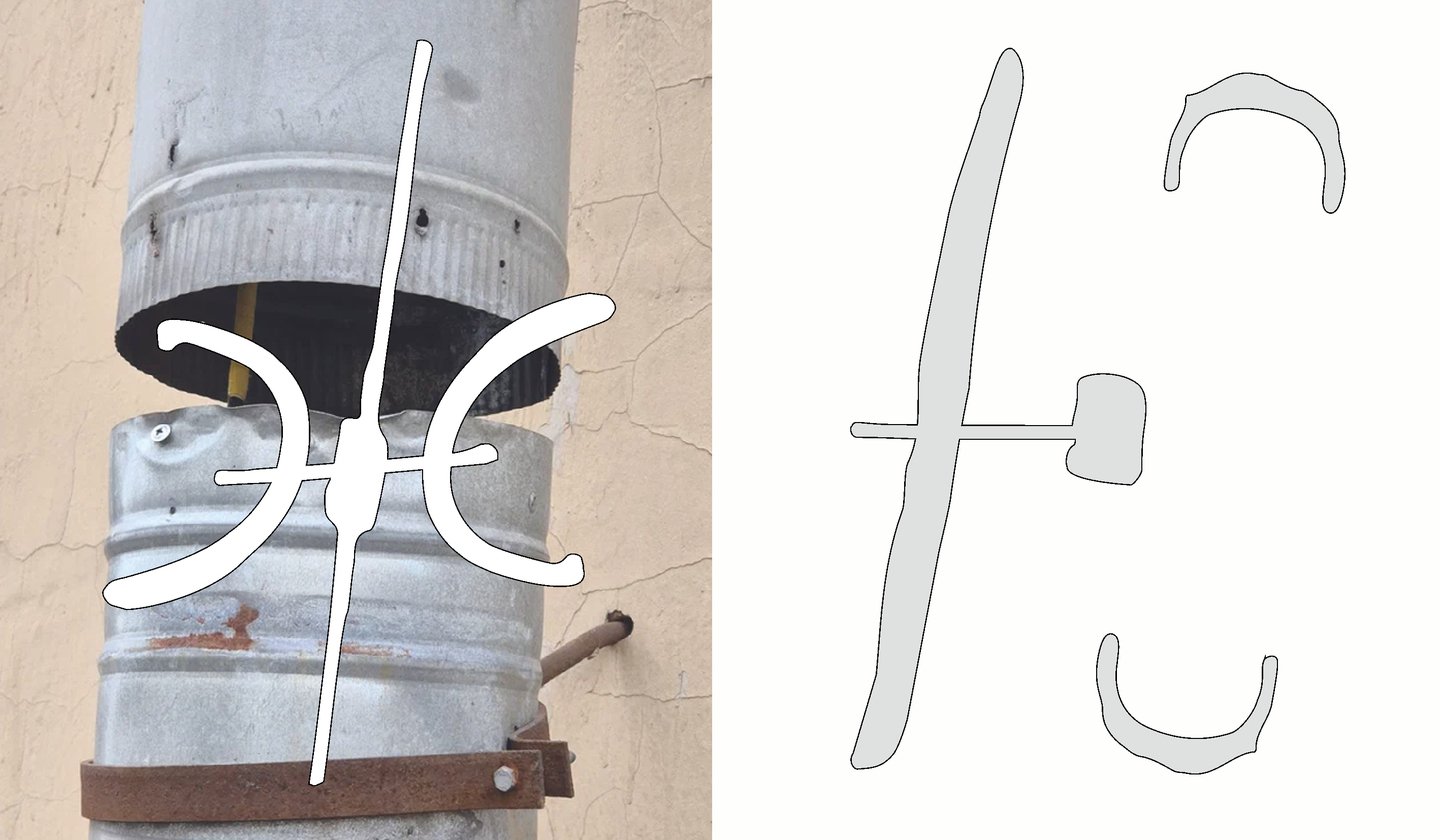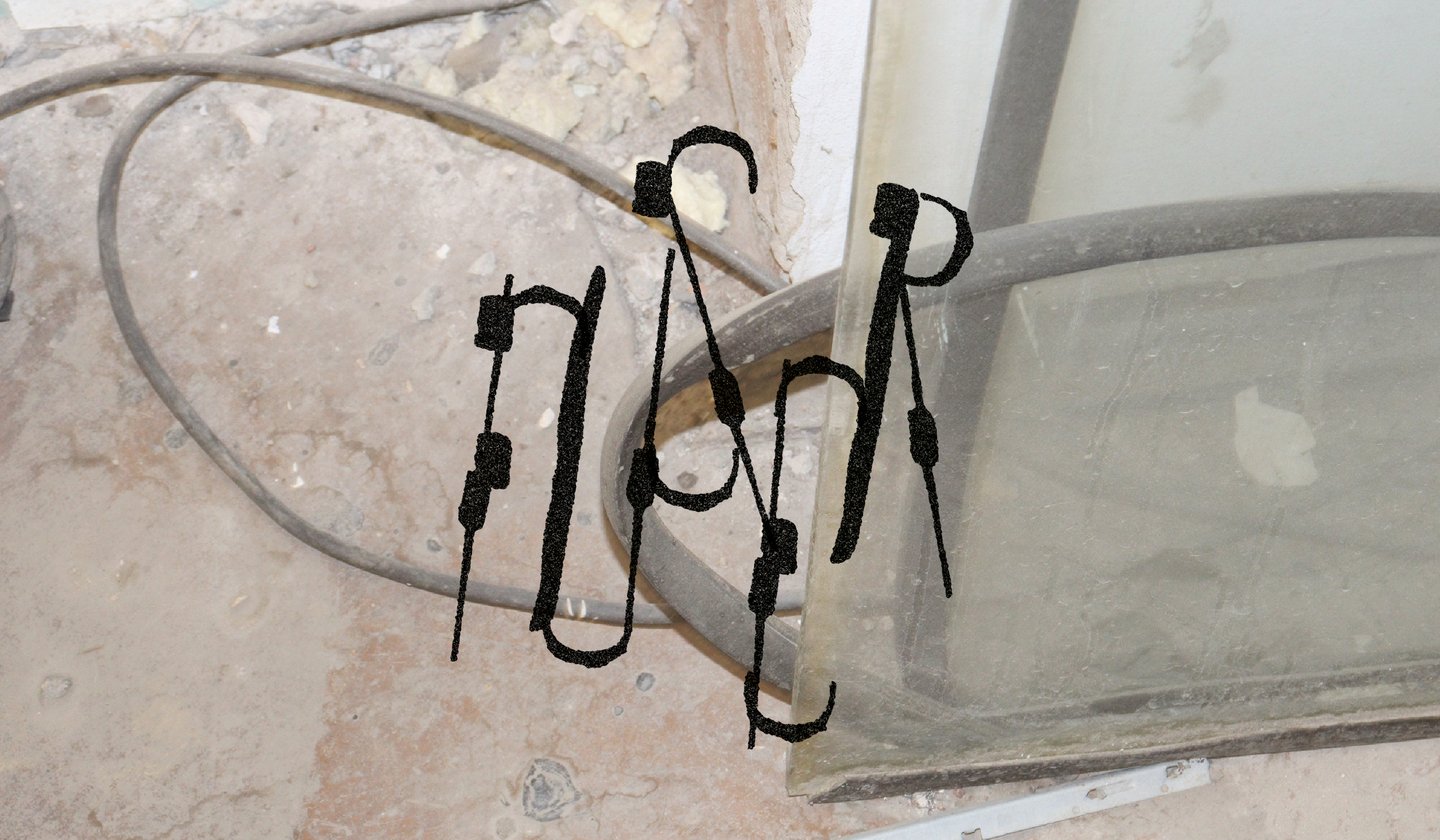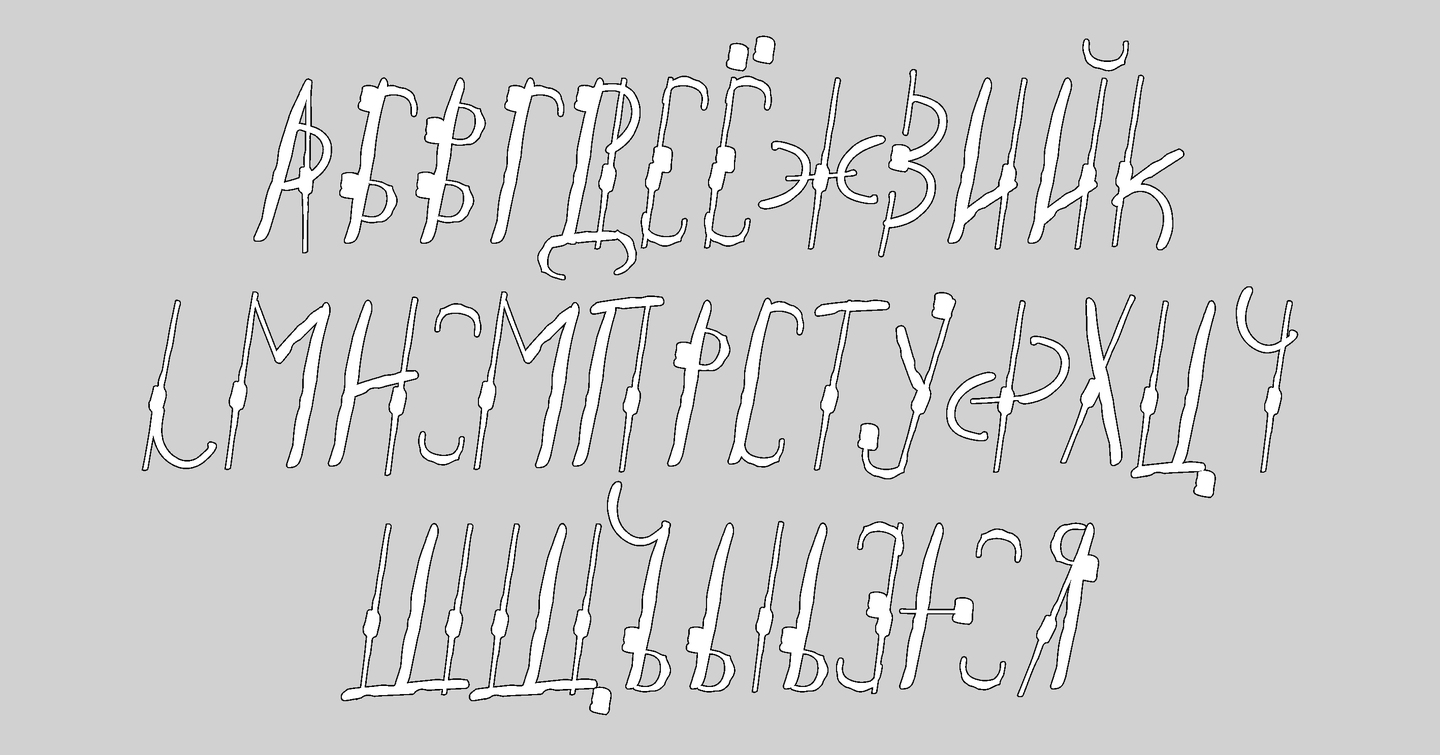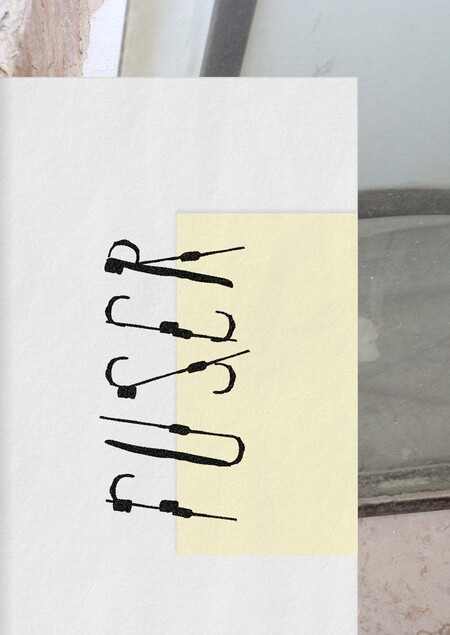
FUSER font
FUSER font — модульный шрифт созданный на основе соединений электрических проводов. Вдохновлен их контрастностью, небрежностью, живостью, и странностью.